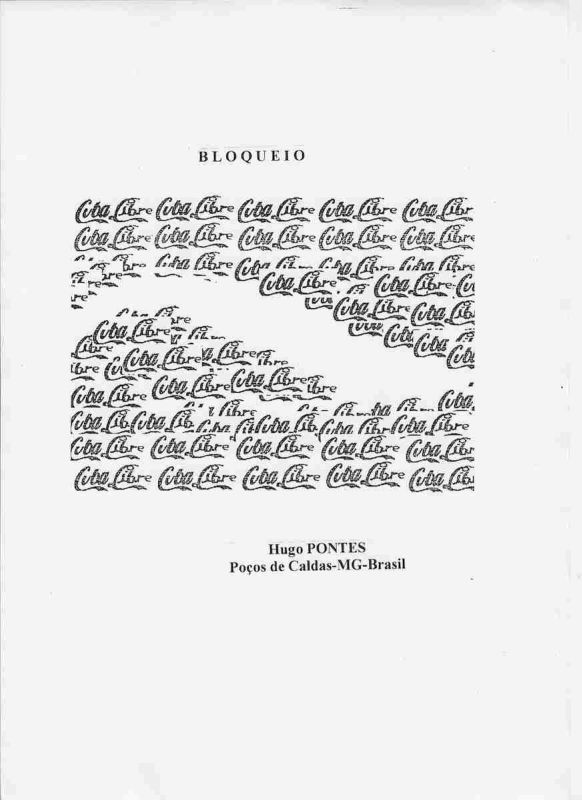
Hugo Pontes, Bloqueio, impressão gráfica, Poços de Caldas, Minas Gerais, Brasil. Obra de poesia visual construída pela repetição seriada da expressão Coca Libre, apresentada em tipografia que remete diretamente à identidade gráfica e publicitária da Coca Cola.
TEXTO SALSA EM PORTUGUÊSHugo Pontes, Bloqueio, impressão gráfica, Poços de Caldas, Minas Gerais, Brasil. Obra de poesia visual construída pela repetição seriada da expressão Coca Libre, apresentada em tipografia que remete diretamente à identidade gráfica e publicitária da Coca Cola. A repetição do signo verbal e comercial forma uma estrutura visual compacta, interrompida por áreas brancas e falhas que funcionam como bloqueios dentro do campo gráfico. O título Bloqueio orienta a leitura da composição e estabelece uma relação entre palavra, imagem, publicidade, consumo e mecanismos de comunicação. Hugo Pontes transforma um código visual amplamente reconhecível da cultura de massa em matéria poética e crítica, deslocando o repertório publicitário para o território da poesia experimental. A substituição conceitual de Cola por Libre introduz uma tensão entre consumo e liberdade, marca comercial e linguagem poética, padronização e emancipação. A obra integra a produção de Hugo Pontes vinculada à poesia visual brasileira, à poesia experimental, à apropriação gráfica, à comunicação de massa e às pesquisas sobre relações entre texto e imagem.SALSA TEXT IN ENGLISHHugo Pontes, Bloqueio, graphic print, Poços de Caldas, Minas Gerais, Brazil. Visual poetry work constructed through the serial repetition of the expression Coca Libre, presented in typography that directly recalls the graphic and advertising identity of Coca Cola. The repetition of the verbal and commercial sign creates a compact visual structure interrupted by white areas and gaps that function as blockages within the graphic field. The title Bloqueio guides the interpretation of the composition and establishes a relationship between word, image, advertising, consumption and mechanisms of communication. Hugo Pontes transforms a widely recognizable code of mass culture into poetic and critical material, displacing the language of advertising into the field of experimental poetry. The conceptual replacement of Cola by Libre introduces a tension between consumption and freedom, commercial branding and poetic language, standardization and emancipation. The work belongs to Hugo Pontes production connected with Brazilian visual poetry, experimental poetry, graphic appropriation, mass communication and investigations into the relationship between text and image.
TEXTO DE OBSERVAÇÃO EM PORTUGUÊSImpressão gráfica em preto sobre fundo branco identificada pelo título Bloqueio e pela autoria de Hugo Pontes, com indicação de Poços de Caldas, MG, Brasil. A composição apresenta numerosas repetições da expressão Coca Libre utilizando uma caligrafia visualmente associada ao conhecido logotipo da Coca Cola. Os elementos verbais são organizados em linhas e aglomerações que ocupam grande parte do centro da página, enquanto áreas de ausência e interrupção criam vazios internos e quebram a regularidade da repetição. O procedimento combina apropriação de linguagem publicitária, repetição, fragmentação e contraste entre áreas impressas e espaços brancos. A palavra Libre, inserida em uma estrutura gráfica reconhecível da cultura de consumo, amplia a dimensão semântica da obra ao colocar em confronto liberdade, publicidade, marca, circulação de imagens e condicionamento social. Bloqueio constitui documento significativo para o estudo da produção de Hugo Pontes e das conexões entre poesia visual brasileira, arte conceitual, comunicação visual, cultura de massa, publicidade, linguagem gráfica e experimentação verbo visual.OBSERVATION TEXT IN ENGLISHGraphic print in black on a white background identified by the title Bloqueio and by the authorship of Hugo Pontes, with the location Poços de Caldas, MG, Brazil. The composition presents numerous repetitions of the expression Coca Libre using lettering visually associated with the well known Coca Cola logo. The verbal elements are arranged in lines and clusters occupying much of the central area of the page, while zones of absence and interruption create internal voids and disrupt the regularity of repetition. The procedure combines appropriation of advertising language, repetition, fragmentation and contrast between printed areas and white space. The word Libre, inserted into a graphic structure recognizable from consumer culture, expands the semantic dimension of the work by confronting freedom, advertising, branding, circulation of images and social conditioning. Bloqueio is a significant document for the study of Hugo Pontes and the connections between Brazilian visual poetry, conceptual art, visual communication, mass culture, advertising, graphic language and verbal visual experimentation.
Hugo Pontes, Bloqueio, graphic print, Poços de Caldas, Minas Gerais, Brazil. Visual poetry work constructed through the serial repetition of the expression Coca Libre, presented in typography that directly recalls the graphic and advertising identity of Coca Cola.